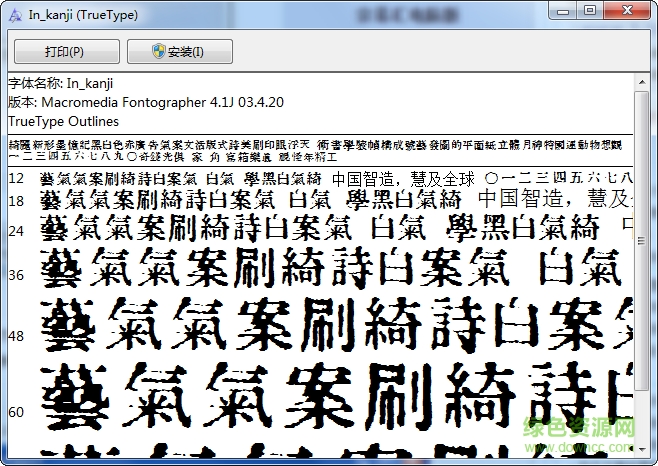
大字報(bào)字體是一款風(fēng)格粗獷的中文字體,文革時(shí)期的宣傳畫字體就是用的這個(gè),在需要制作一些歷史性的畫報(bào)或海報(bào)時(shí),這款字體還是很實(shí)用的。
文革大字報(bào)以及戶外宣傳中所用到的字體,是一種較為獨(dú)特的美術(shù)字。當(dāng)時(shí)沒有電腦,都是靠手繪的美術(shù)字,這種字體使用極為粗獷的筆觸,黑體并帶有少許裝飾結(jié)構(gòu),紅色為主的顏色。其最終的目的就是醒目、易于識(shí)別。加之簡(jiǎn)化漢字已經(jīng)開始普及(有些用到了更為簡(jiǎn)化的第二代簡(jiǎn)化字,但是這種簡(jiǎn)化字現(xiàn)在并沒有被應(yīng)用),使這種字體更具標(biāo)題性、號(hào)召性、革命性。